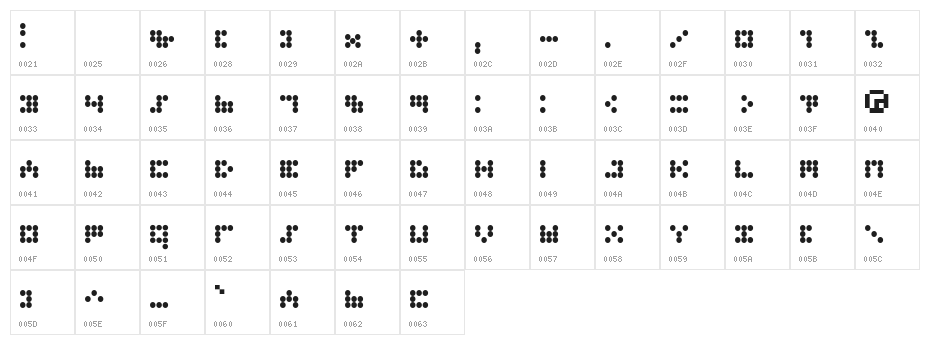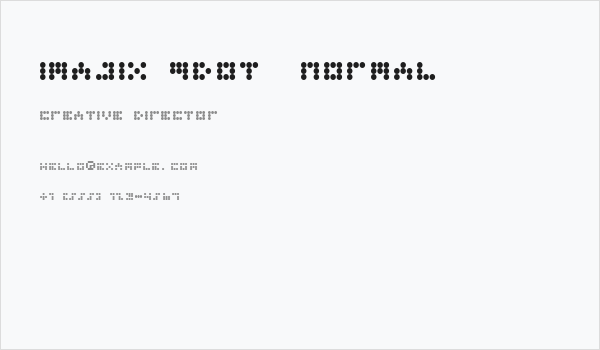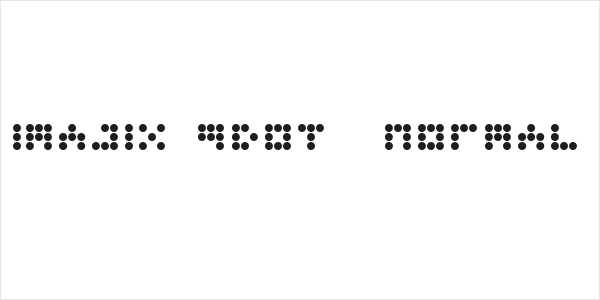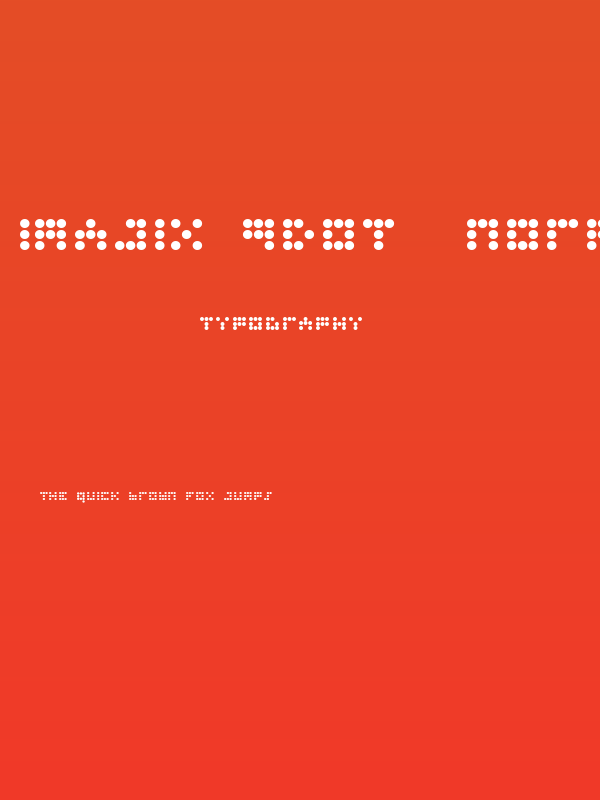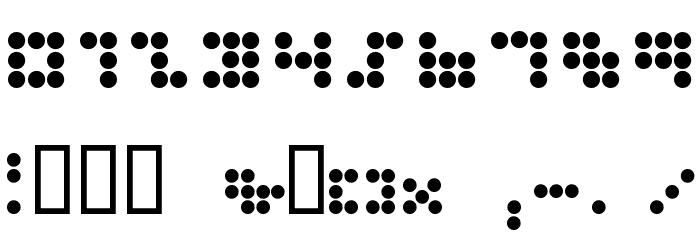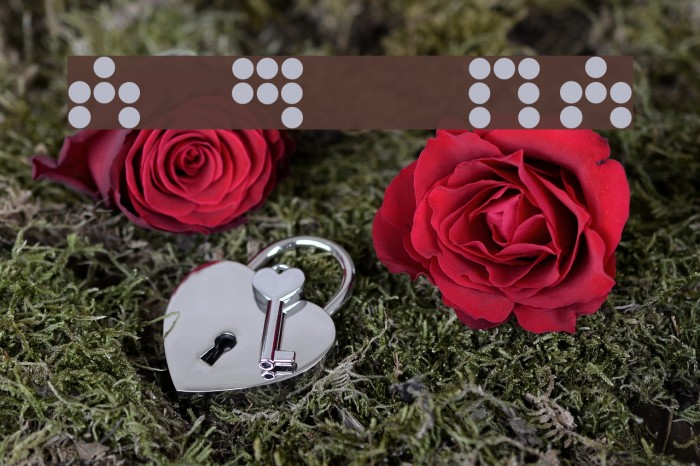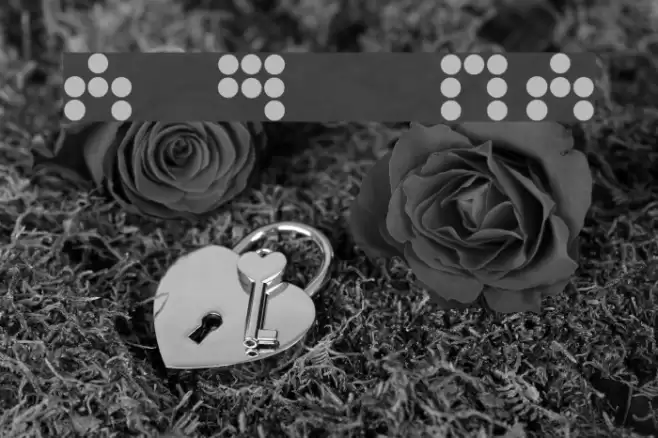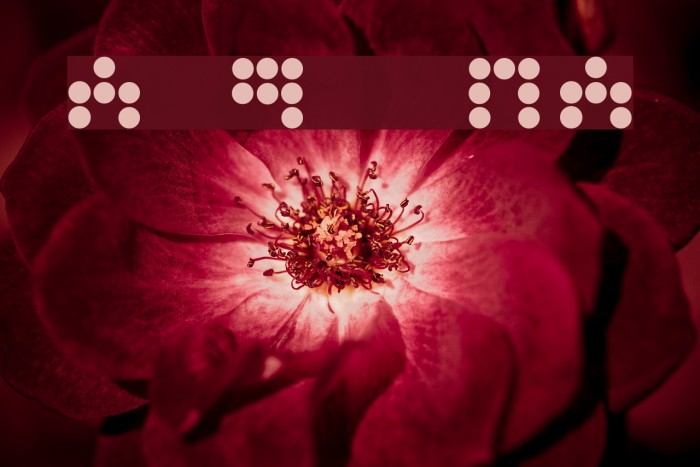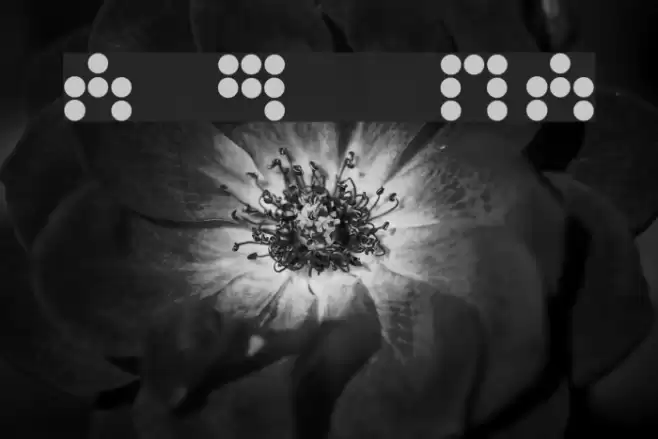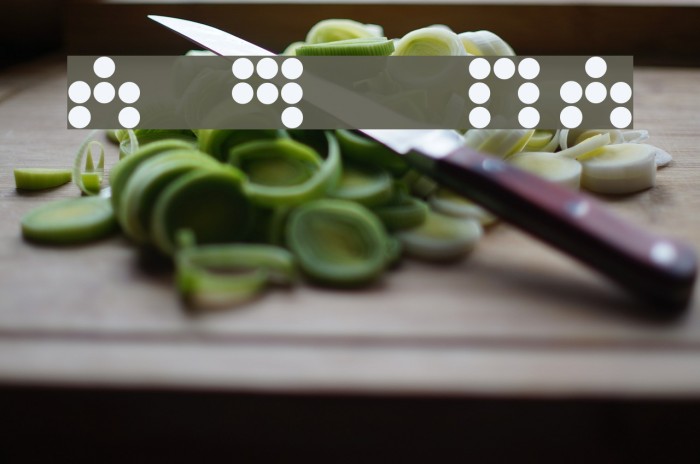
imajix 9dot Normal Font
| Nom | imajix 9dot Normal |
| Poids | Normal |
| Cas d'utilisation | Headlines, Logos, Digital interfaces |
| Projets proposés | Ideal for digital displays, tech-themed designs, video game interfaces, and futuristic branding. |